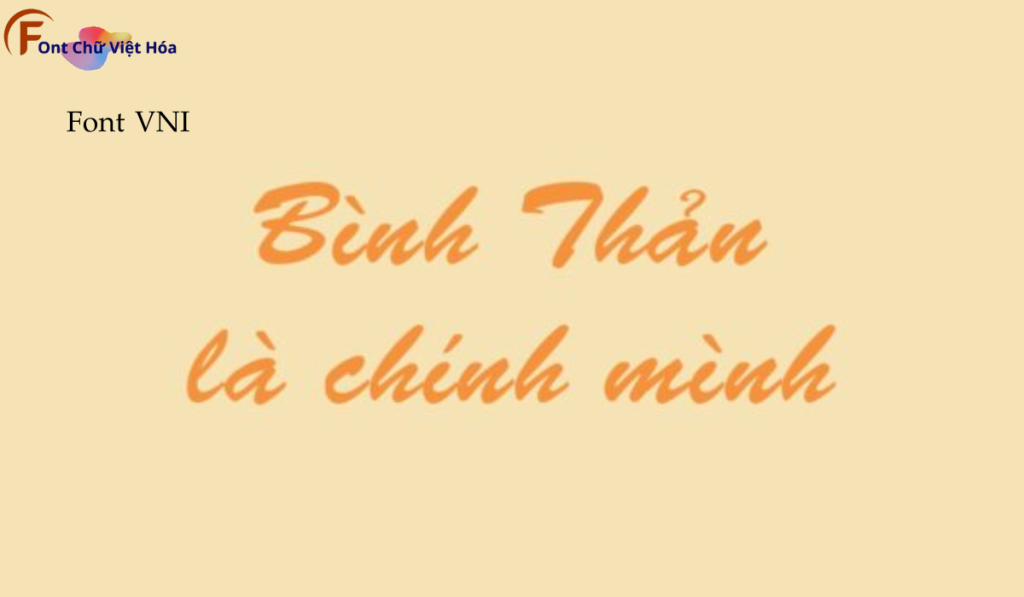
Font VNI Brush Việt Hóa
Phân loại: Cá tính, độc đáo
Kiểu chữ: Chữ thảo
Độ dày: Thường
Font VNI Brush Việt Hóa, thuộc bộ font VNI, mang phong cách viết tay mạnh mẽ và cá tính, phù hợp cho các dự án thiết kế như poster, logo, và bao bì sản phẩm. Với các nét chữ uyển chuyển và độ dày đều đặn, Font VNI Brush Việt Hóa không chỉ dễ đọc mà còn tạo cảm giác nghệ thuật và sáng tạo. Việc Việt hóa font giúp người dùng dễ dàng tích hợp vào các thiết kế tiếng Việt, mang lại sự tiện lợi và nâng cao tính thẩm mỹ.